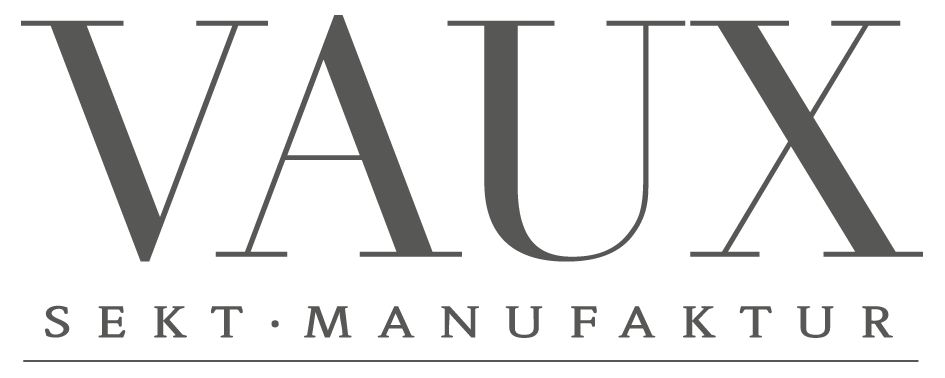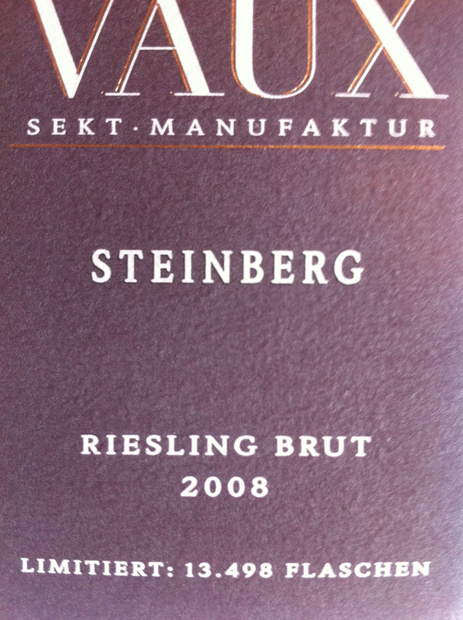
Suche Typo von Schloss VAUX Etiketten
Ich bin auf der Suche nach der Haustypo von Schloss VAUX, die u.a. für die Subline im Logo und auf den Etiketten verwendet wird. Ich habe ein Foto des Flaschenanhängers hochgeladen.
Ich dachte zuerst es wäre die FF Eureka, aber die Serifen sind weniger ausgeprägt und es scheint einen Condensed- (bzw. einen Extended-) Schnitt zu geben.
ITC Weidemann wäre meine Vermutung. Die Subline sieht verzerrt aus …
Das Logo habe ich jenem pdf entnommen.